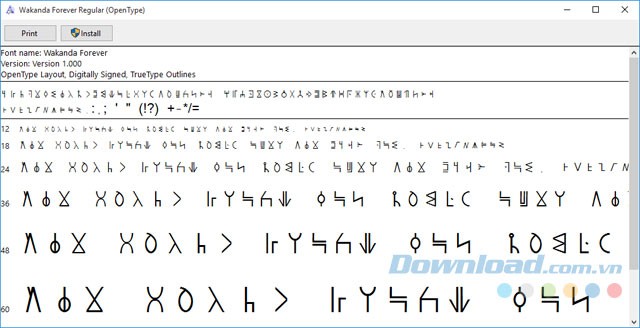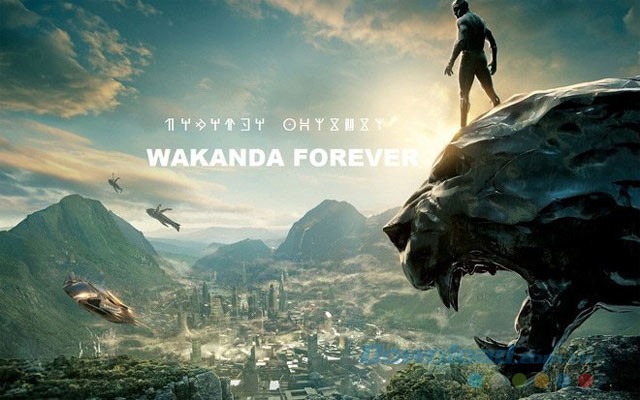
Nguồn Cảm Hứng Từ Wakanda: Bộ Font Chữ Độc Đáo
Bộ font Wakanda Forever được hình thành dựa trên ngôn ngữ Wakanda hư cấu, mang đậm tính biểu tượng và được giới thiệu trong bộ phim Black Panther (Chiến binh báo đen) đầy thành công.
Với bộ font này, việc thiết kế và tạo ra các poster mang phong cách riêng trở nên dễ dàng hơn bao giờ hết, nhờ vào những ký tự cổ đại có hình dáng độc đáo.
Adam Shady, một nhà thiết kế tài năng đồng thời là thành viên tích cực của Dribbble – nền tảng trực tuyến hàng đầu dành cho cộng đồng designer toàn cầu – đã bắt đầu quá trình chuyển đổi bảng chữ cái Wakanda từ phim thành một bộ font chữ hoàn chỉnh.
Mục đích của việc này là mang đến cho người dùng công cụ để tự do sáng tạo và thể hiện ý tưởng.
Tuy nhiên, cần lưu ý rằng bộ font Wakanda Forever hiện tại không tương thích với tiếng Việt. Điều này có thể dẫn đến các vấn đề về khoảng cách giữa các ký tự.
Adam Shady đã nhận thức được hạn chế này và đang nỗ lực khắc phục trong các phiên bản cập nhật sắp tới.
Khám phá những điểm nổi bật của bộ font Wakanda Forever
- Bộ font Wakanda Forever sở hữu vẻ đẹp độc đáo, với những đường nét tượng hình ấn tượng.
- Kiểu chữ tinh tế này đặc biệt phù hợp cho các dự án thiết kế như bìa sách, áp phích quảng cáo.
- Bộ font hoàn chỉnh bao gồm đầy đủ các ký tự, con số và dấu câu cần thiết.
Font chữ này không chỉ là một công cụ thiết kế, mà còn là một cách để thể hiện sự yêu thích đối với văn hóa và thế giới quan trong phim.
Hãy để Wakanda Forever trở thành nguồn cảm hứng sáng tạo cho những dự án nghệ thuật của bạn.